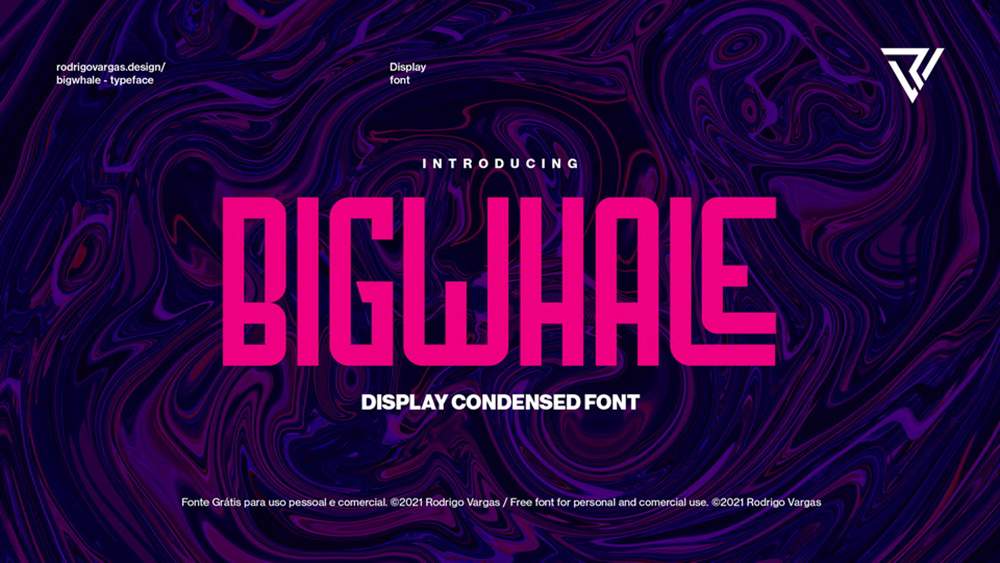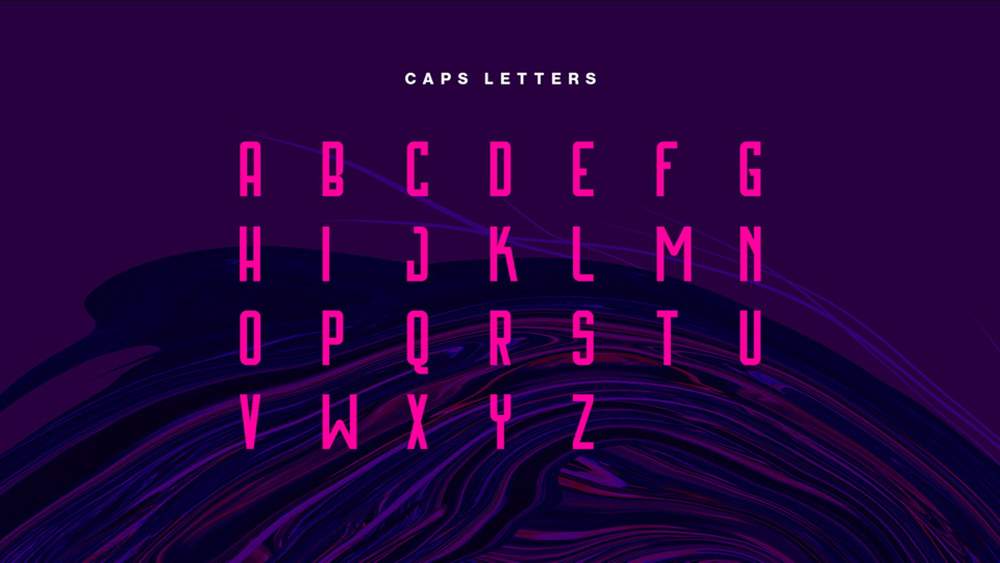
فونت پرمیوم و انگلیسی Bigwhale Font یک فونت نمایشی فشرده است. این فونت برای استفاده در عناوینی با مجموعهای از اعداد، نمادهای پایه و علائم نگارشی عالی است. همچنین برای برخی از مجموعههای حروف، برای سفارشیسازی بیشتر طرحهای شما، دارای بانداژهایی است.
مزایای استفاده از فونت لاتین Bigwhale چیست؟